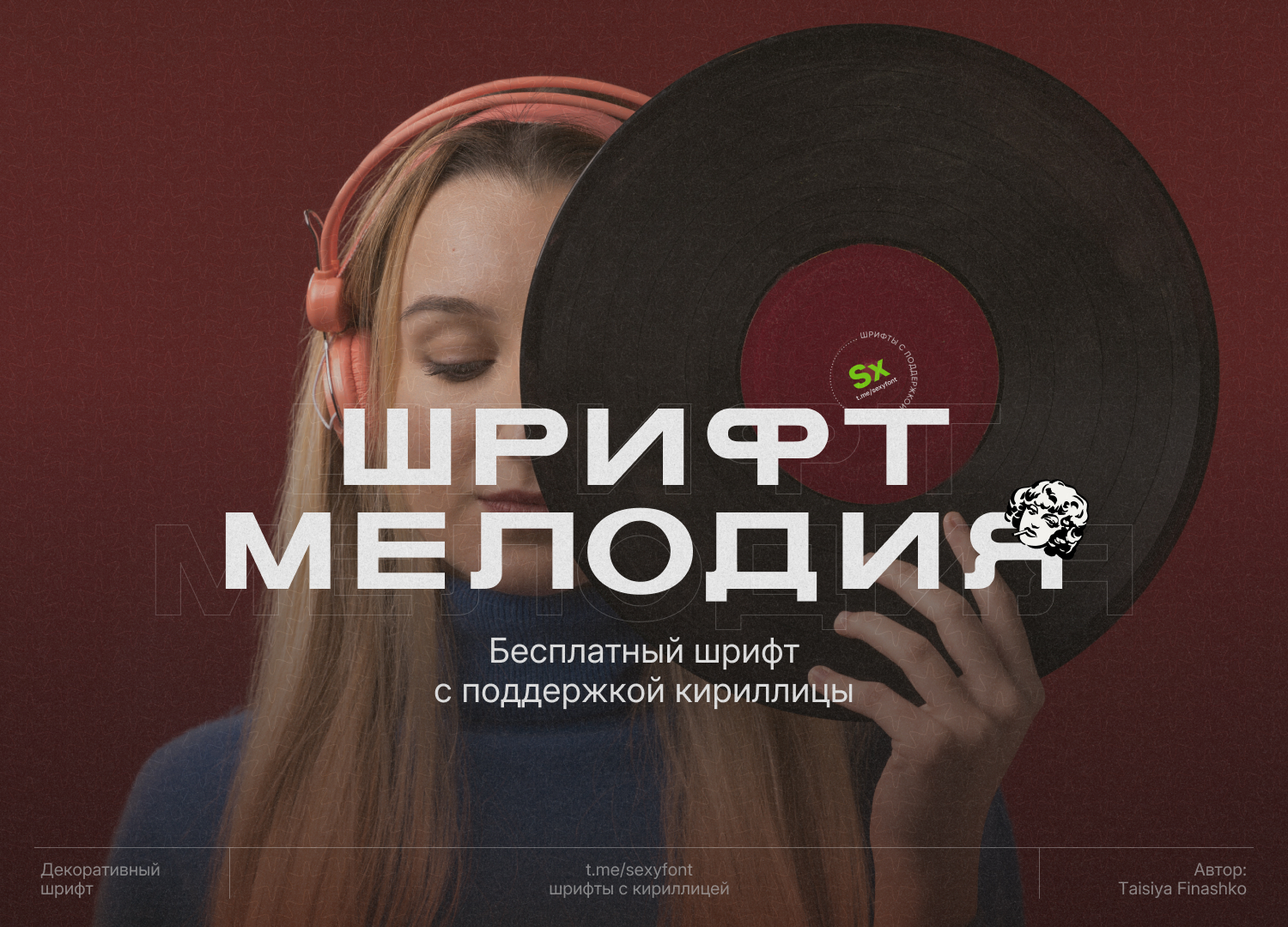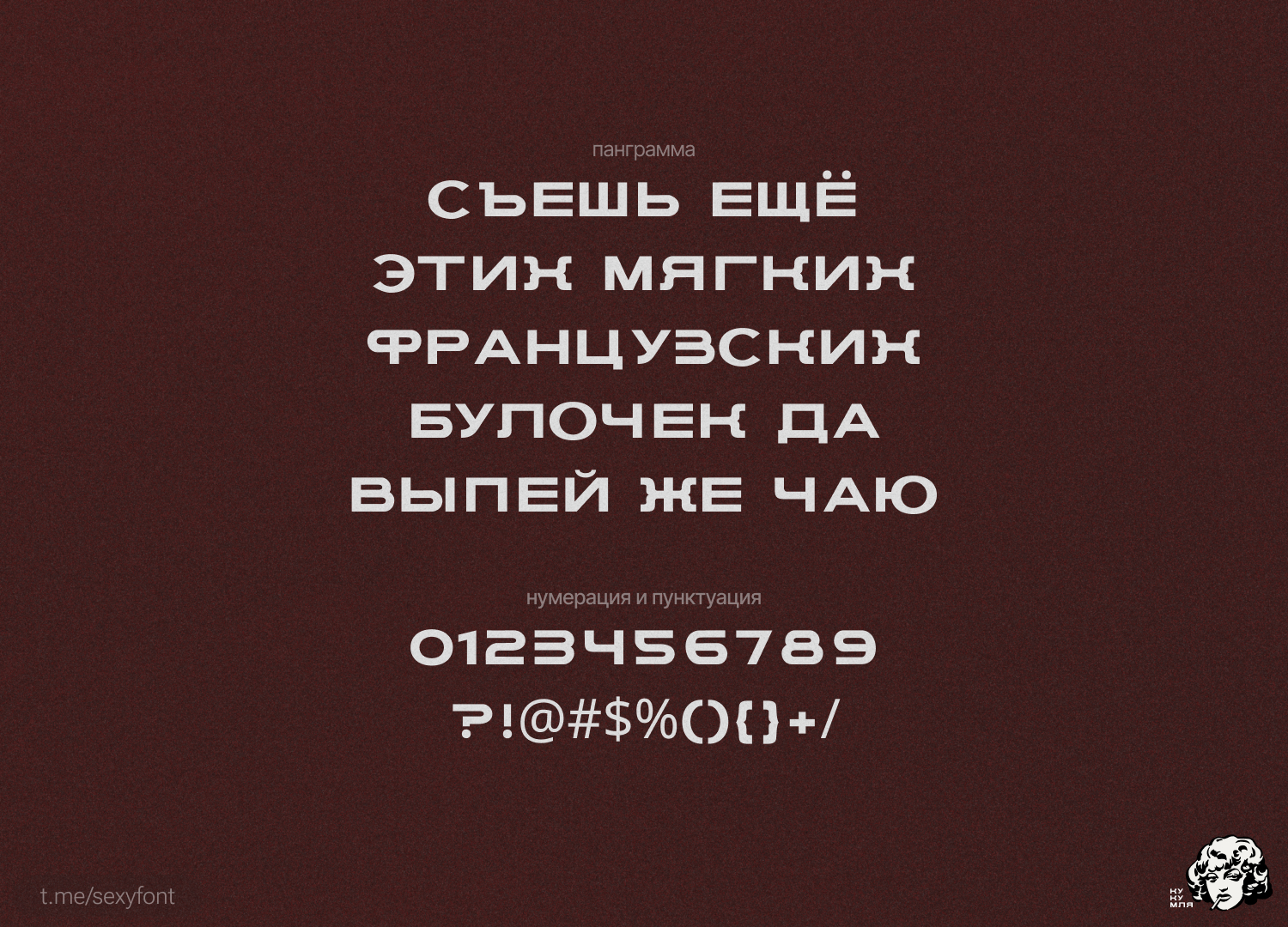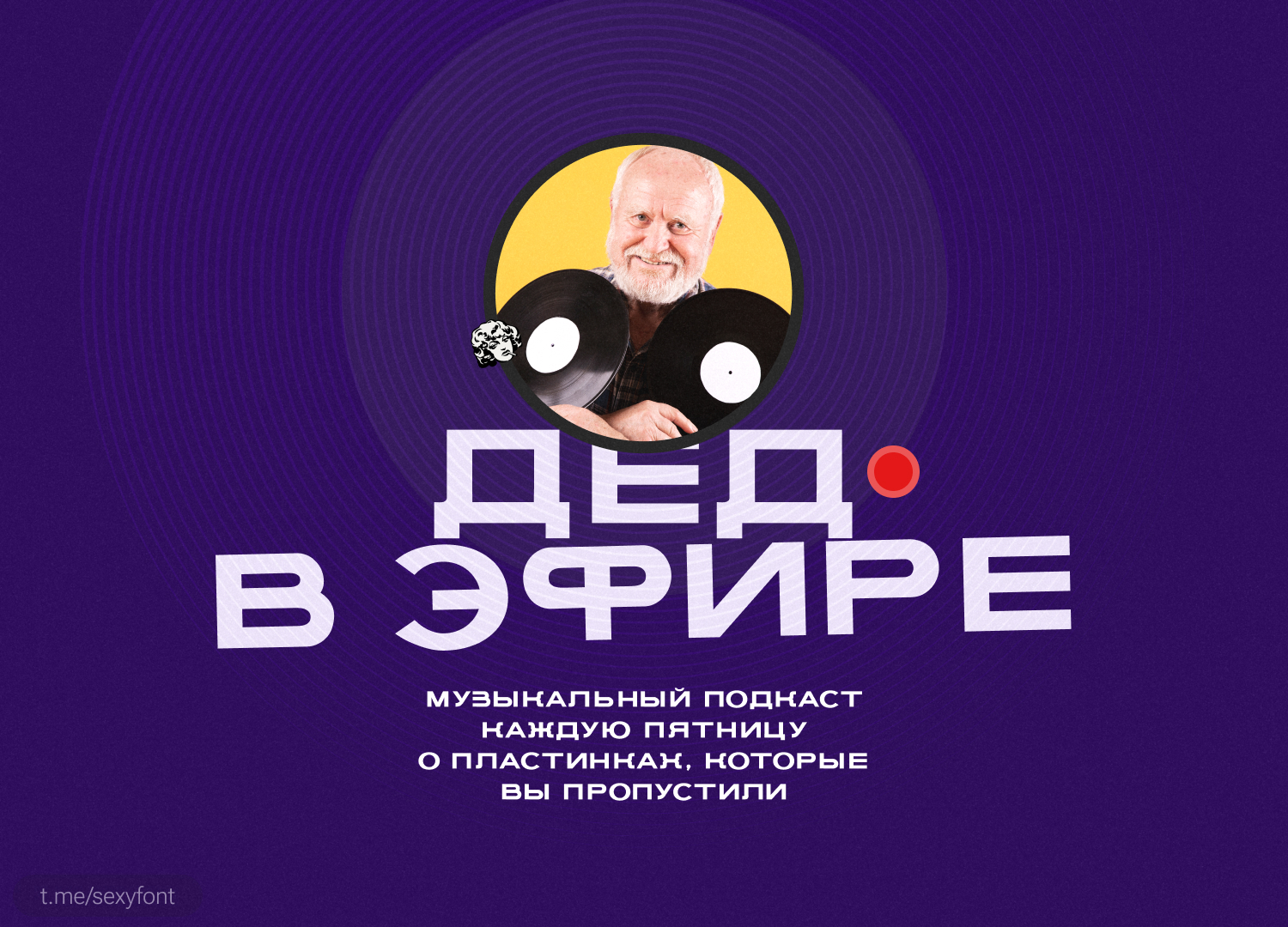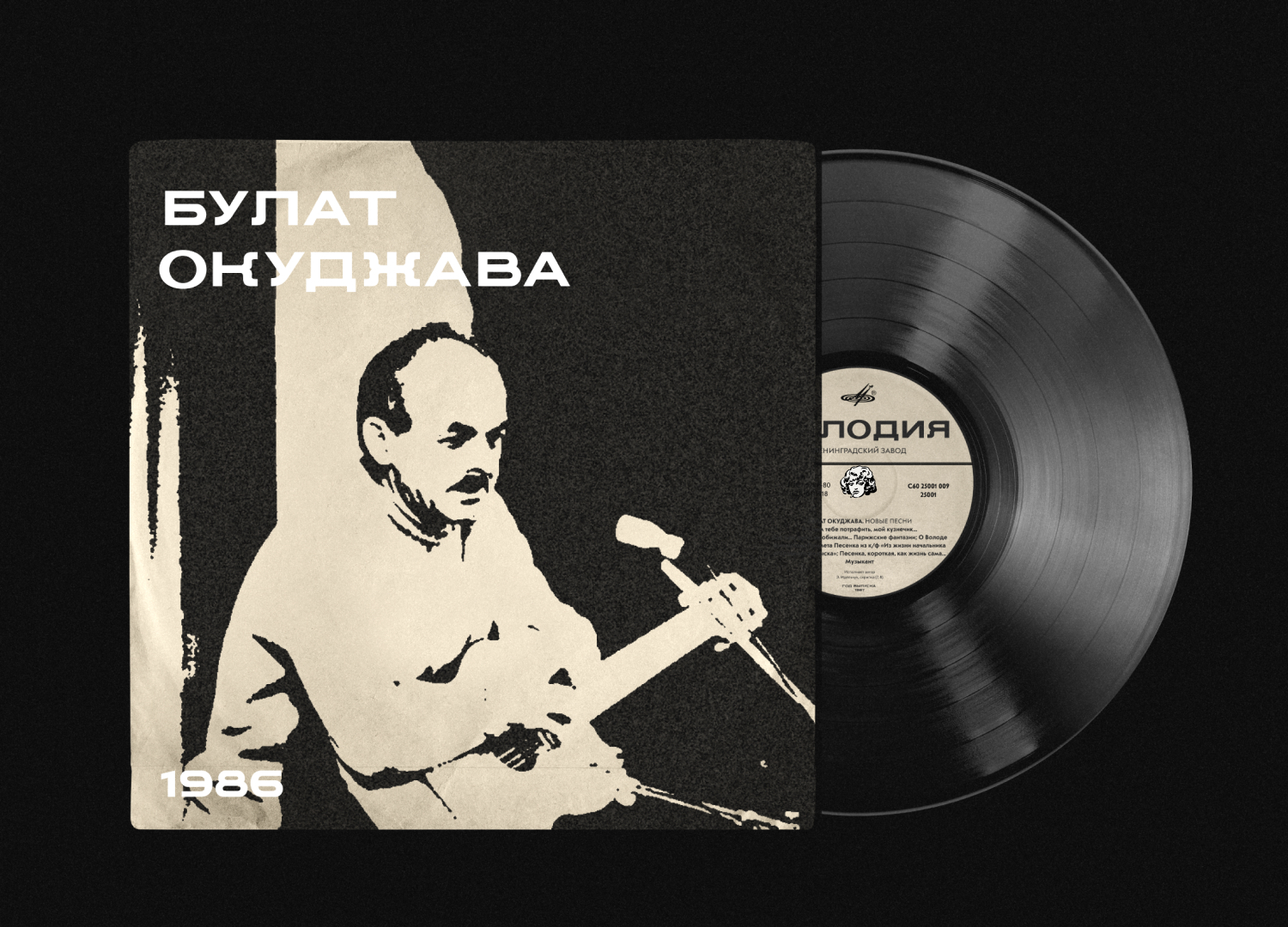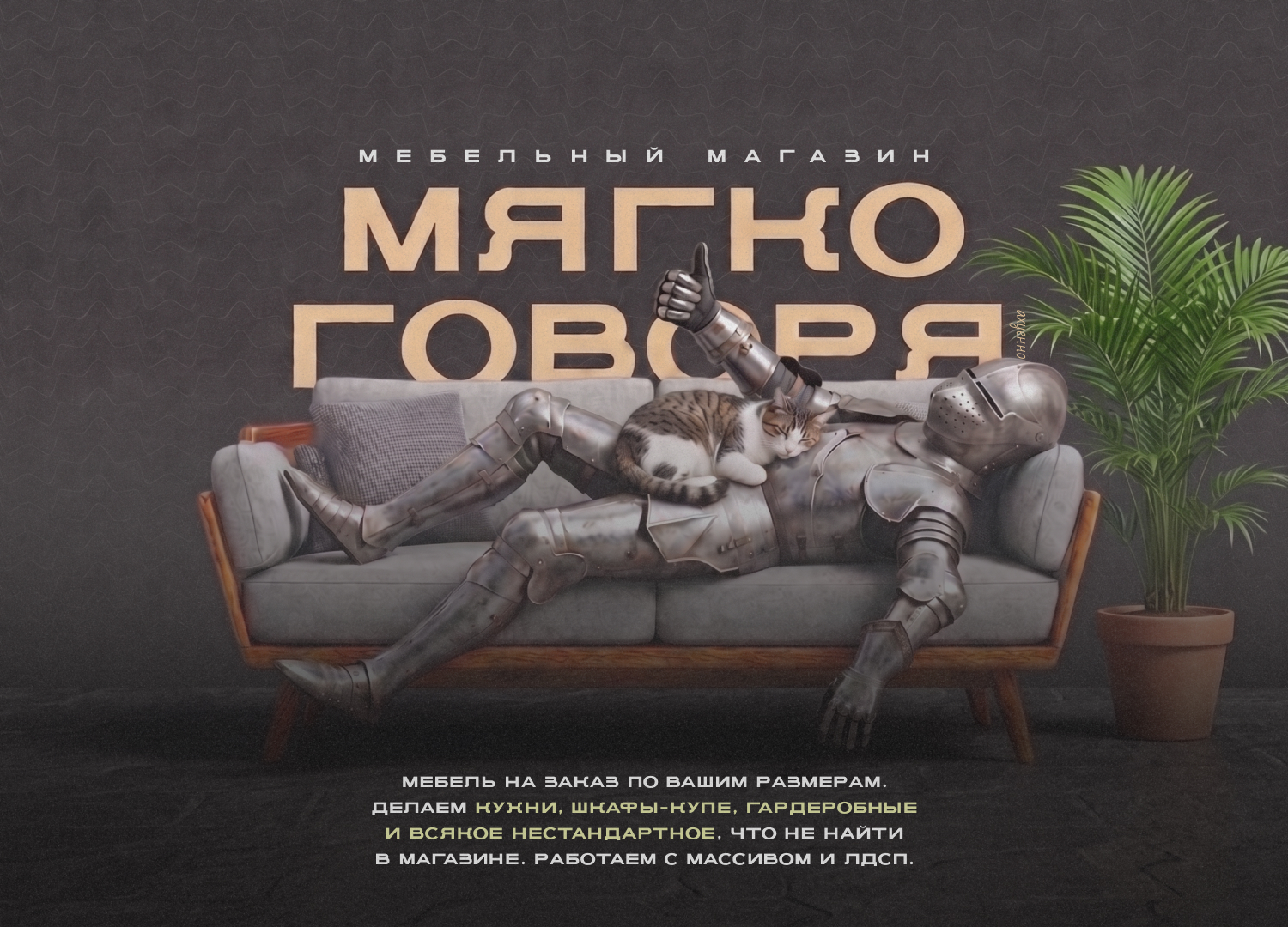
Шрифт melodi⁠⁠
Привет. Лови еще один шрифт. Называется melodi. Жирный квадратный гротеск с лёгким ретро-душком. Плотный, тяжёлый, немного в духе старых вывесок.